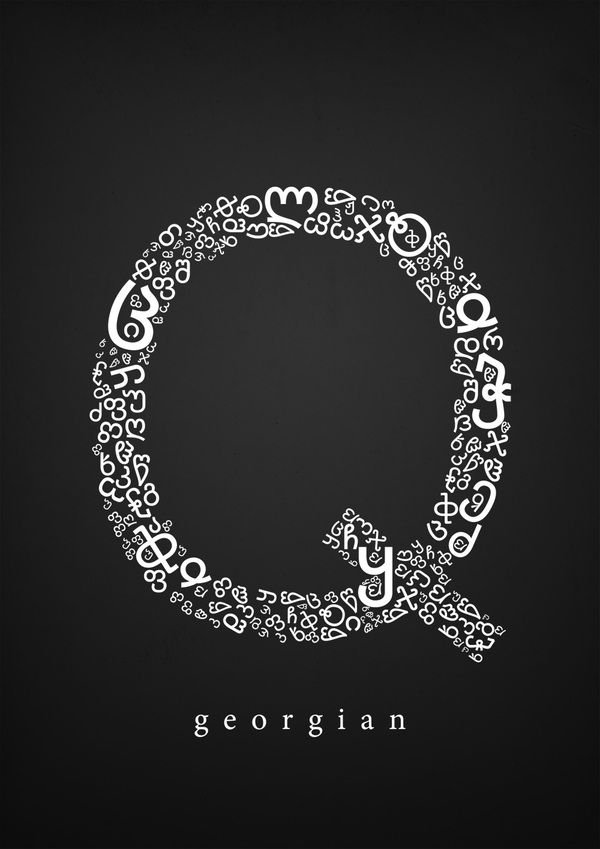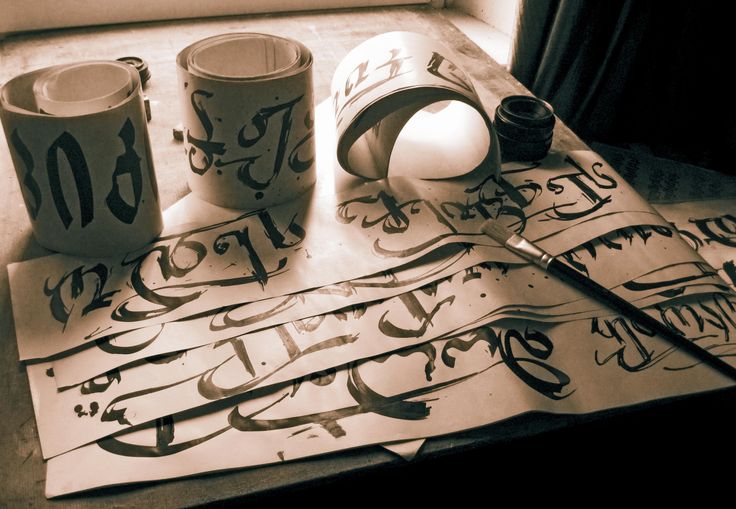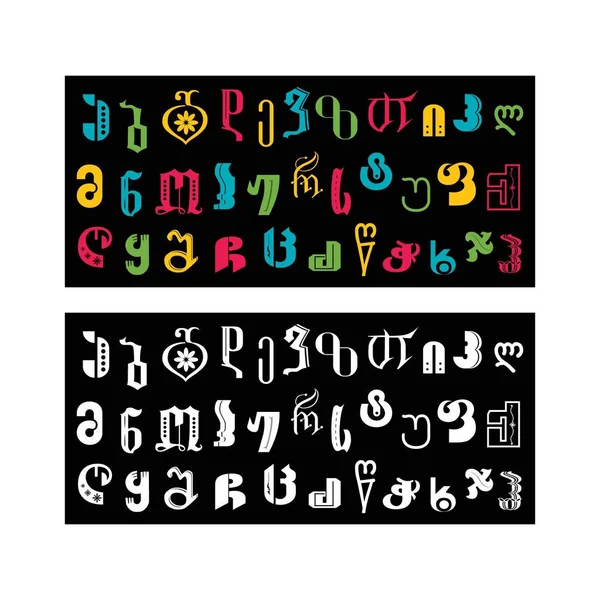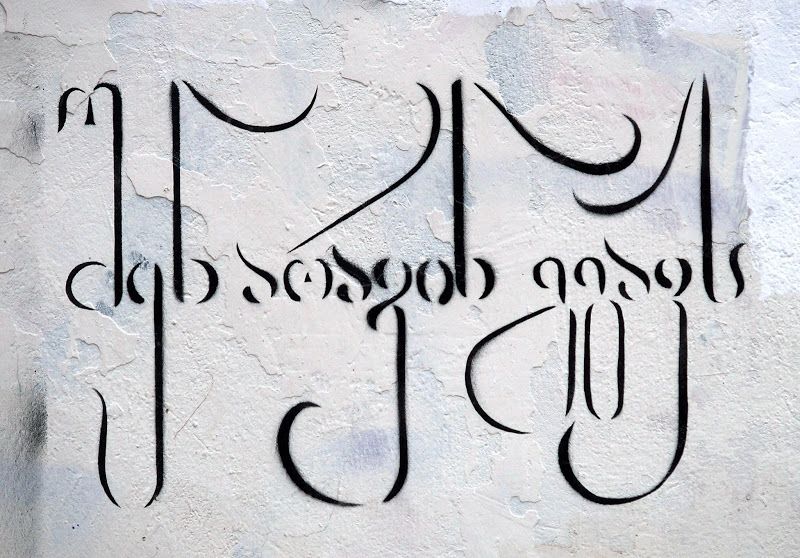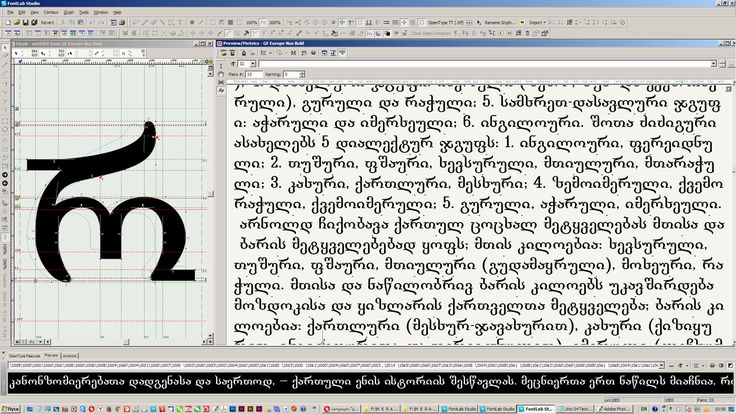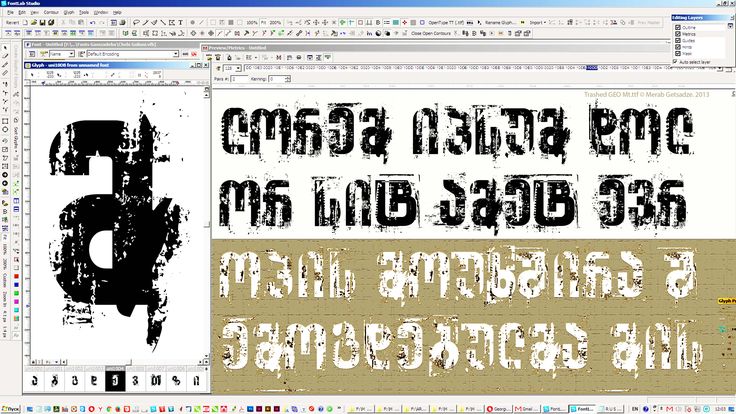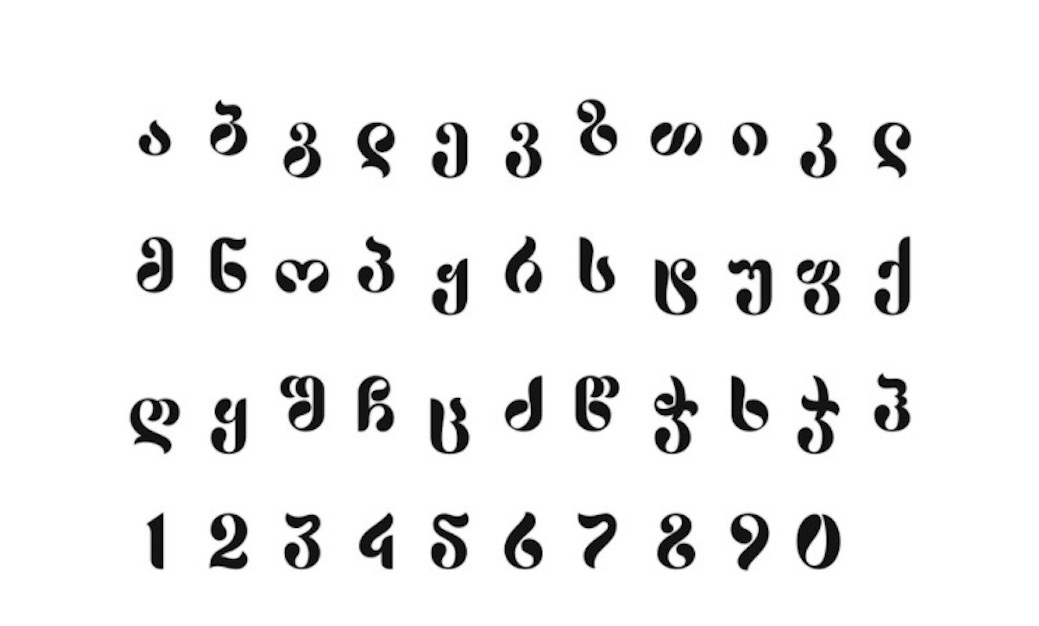
«Грузинская типографика наверстывает упущенное» Что происходит со шрифтами в Грузии?
Мы выпустили грузинскую версию Graphik и решили узнать, как устроена сегодняшняя грузинская типографика. Что было утрачено в первые постсоветские годы, почему в Грузии легче получить заказ на фирменный шрифт, чем продать качественный тиражный, и что будет дальше — отвечают грузинские дизайнеры
В июне 2018 года для грузинской типографики произошло важное событие: после долгих лет обмена письмами в мировой стандарт Юникод были добавлены глифы для мтаврули, вида грузинского письма, который можно с натяжкой сравнить с прописными буквами в кириллице или латинице.
До обновления утвердившего мтаврули в Юникоде уже было три грузинских алфавита: асомтаврули, нусхури и мхедрули. Первые два — древние церковные формы письма, сейчас они в основном используются Грузинской православной церковью, в иконографии, в настенной росписи и вообще везде, где важно подчеркнуть древность, — приблизительно как устав и полуустав в кириллице. В повседневной жизни в основном используется мхедрули — так повелось ещё с XI века, когда этим стилем начали писать большинство нецерковных, секулярных текстов: он проще в чтении.
Евангелие написанное асомтаврули, IX век
Псалтырь написанный асомтаврули, X век ![nus1]Выдержки из Евангелия написанные нусхури, XIV–XV век Завещание царя Давита IV Шио-Мгвимскому монастырю, написанное нусхури.
XII векФото из Национальных архивов Грузии
В отличие от асомтаврули и нусхури, где есть прописные и строчные, у мхедрули всегда был только один регистр. Лишь в середине XIX века были разработаны гарнитуры с отдельным стилем мтаврули для прописных букв. С использованием мтаврули писатель и педагог Яков Гогебашвили напечатал «Деда эна» — иллюстрированный букварь, по которому полтора столетия учились все дети в грузинских школах. На грузинских пишущих машинках присутствовали и мхедрули, и мтаврули — по аналогии со строчными и прописными в других письменностях. Но начиная с 1920-х годов мтаврули стали использовать только для печати заголовков и для маюскульного письма, когда все буквы в слове написаны прописными.